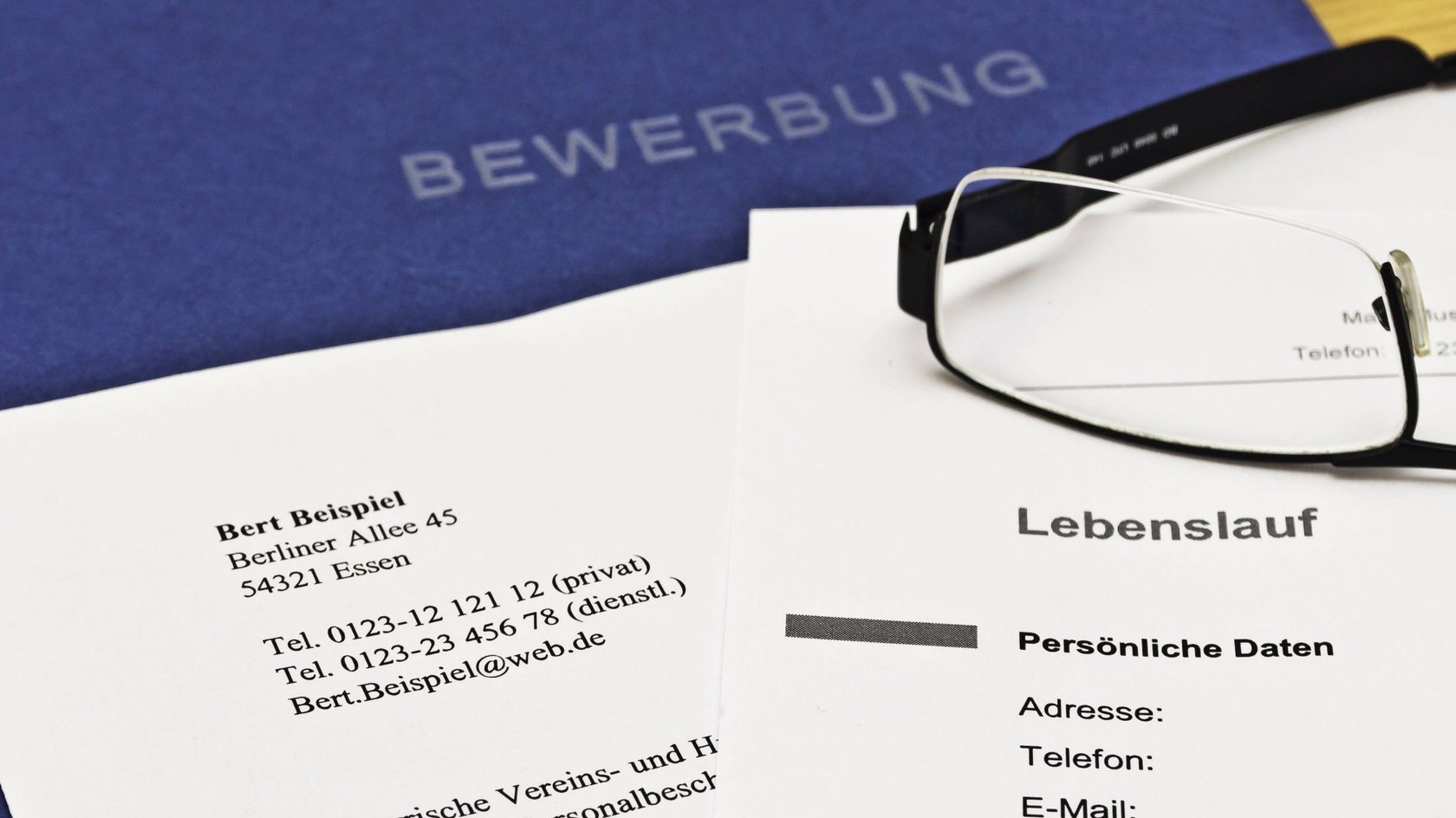
Praxistipp: Welche Schriftart zur Bewerbung?
Man sollte verschiedene Schriftarten in einer Bewerbung vermeiden. (© IMAGO / Zoonar)
Mit seiner Bewerbung will man einen seriösen Eindruck machen. Daher empfiehlt sich ein einheitliches und ausgewogenes Erscheinungsbild. Auch die Schriftart der Bewerbung spielt eine Rolle. Hier ein paar Tipps!
Abgesehen von besonders kreativen Berufen, bewirbt man sich mit Bewerbungsschreiben, die eher sachlich und einfach erscheinen. Sie sollten sich an die üblichen Maßgaben halten und alle wichtigen Informationen zusammenfassen. In der Regel landen Bewerbungen bei Personalsachbearbeitern, die einen üblichen Stil erwarten, der sich hinsichtlich der Gestaltung und Aufteilung nicht zu sehr abhebt.
Die ideale Schriftart für die Bewerbung?
Klassisch und unaufdringlich sollte eine Bewerbung sein. Klare Vorschriften für die Schriftarten einer Bewerbung gibt es nicht, nur Empfehlungen. Und die wichtigste Empfehlung lautet:
Alle Seiten der Bewerbung sollten in derselben Schriftart sein! Egal, ob Deckblatt, Lebenslauf oder das eigentliche Anschreiben. Jede Seite sollte in der gleichen Schrift formatiert sein.
Eine ideale Schriftart gibt es ebenfalls nicht. Allerdings noch einen Ratschlag. Unbedingt verzichten solltet ihr auf verspielte Schriften oder die gruselige Schriftart Comic Sans (für die sich der Designer der Schrift mittlerweile schämt). Die klassischen Schriften unterteilen sich in zwei Klassen. Da sind die Serifenschriften und die serifenlosen Schriften. Beide sind brauchbar, solange man keine Schriftarten mischt.
Serifenschriften, wie etwa Times Roman oder Bookman zeichnen sich durch kleine Striche an den Enden der Schriftlinien aus. Das sind die sogenannten Serifen. Solche Schriften sind häufig im Buchdruck zu finden. Sie sind gut lesbar und machen einen seriösen Eindruck.
Bewerbung in drei Schriftarten - wer kriegt den Job nicht?
Auch serifenlose Schriften machen einen guten Eindruck. Bekannte Beispiele sind Arial, Calibri oder Verdana. Sie sind auf jedem PC enthalten und man kann mit Ihnen nichts falsch machen. Im obigen Bild sieht man das Wort Bewerbung in drei verschiedenen Schriftarten. Ganz oben in Comic Sans, die man gewöhnlich eher auf den Festplakaten von Schrebergärten findet. Darunter in Times New Roman, einer Serifenschrift. Der Vertreter der serifenlosen Schriften ist in dem Fall Arial, ebenfalls ein Windows-Standard. Alle drei Schriftarten sind in derselben Schriftgröße. Jede wirkt anders.
Noch ein Tipp
Worauf man als Bewerber keinerlei Einfluss hat, sind die Schriftarten und die Erscheinung von Zeugnissen und ähnlichen Dokumenten. Sie stammen von Schulen, früheren Arbeitgebern oder anderen Stellen. Es ist nicht schlimm, wenn die alle unterschiedlich gestaltet sind. Hier kommt es auf den Inhalt an. Wenn man allerdings sein Zeugnis selbst geschrieben hat, was so mancher Arbeitgeber anbietet, dann sollte man vielleicht gleich dieselbe Schriftart nehmen oder zumindest in der gleichen Klasse bleiben. Also entweder Serifen oder serifenlos.
Bewerbung: Schriftarten und Schriftgrößen
Bei den Schriftarten einer Bewerbung muss man also Zurückhaltung üben und sich auf eine beschränken. Aber auch die Schriftgröße in der Bewerbung sollte an die Regel der sachlichen Zurückhaltung halten. Auf dem Deckblatt kann man ruhig noch größere Schriften verwenden, damit die wenigen Informationen nicht verloren auf der Seite umherdümpeln. Doch im Fließtext der Bewerbung arbeitet man besser mit einer gut lesbaren Größe und angepassten Überschriften.
Tipp für die Schriftarten der Bewerbung: Weniger ist mehr!
Bei gedruckten Texten ist eine Schriftgröße von 12 Punkt gut lesbar. Das gilt auch für die üblichen Schriftarten einer Bewerbung. Eine Größe von 11 Punkt geht auch noch, wenn man Platz sparen muss. Das kann beispielsweise dann angeraten sein, wenn nur noch ein oder zwei Zeilen auf die nächste Seite rutschen würden. Kleiner sollte die Schriftgröße des Hauptinhaltes aber nicht sein.
Die Überschriften erster Ordnung (Haupt-Überschriften) und zweiter Ordnung (Unter-Überschriften) sollten sich um jeweils zwei Punkte von der Hauptschriftgröße unterscheiden. Daraus ergibt sich also solch ein Standard-Muster für Schriftarten und Schriftgrößen einer Bewerbung:
• Inhalt: 12 Punkt (bei Platzmangel 11 Punkt)
• Neben-Überschriften: 14 Punkt (bei Platzmangel 13 Punkt)
• Haupt-Überschrift: 16 Punkt (bei Platzmangel 15 Punkt)
Die Haupt-Überschrift wird in der Regel nur einmal pro Inhaltsblock (Bewerbung, Lebenslauf) eingesetzt. Die Unterüberschriften können Bedeutungsblöcke innerhalb der Bewerbung gliedern.
Die wichtigste Regel bei den Bewerbungs-Schriftarten und -Schriftgrößen: Weniger ist mehr!